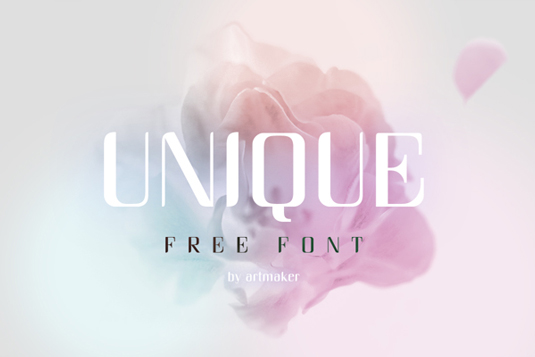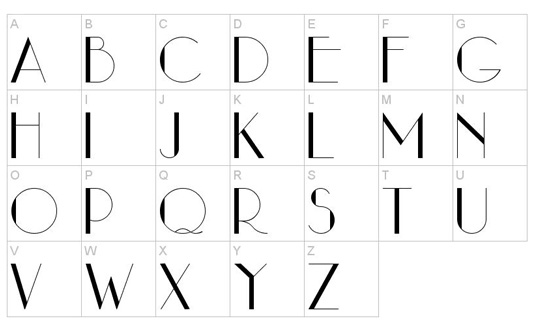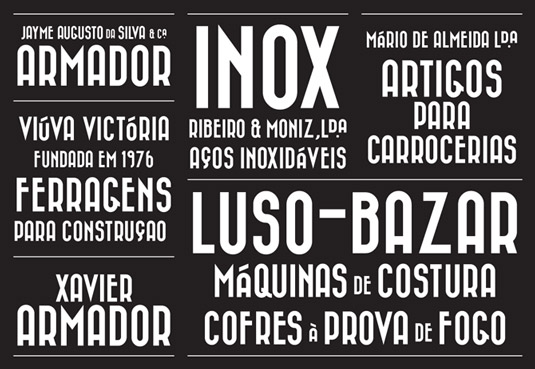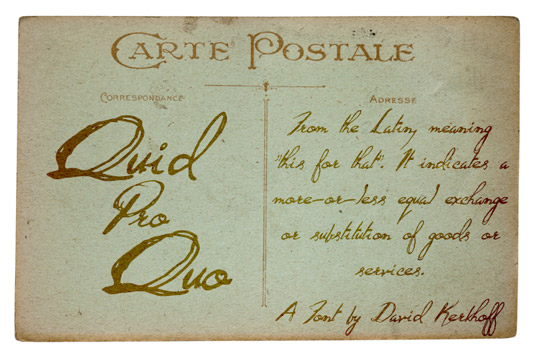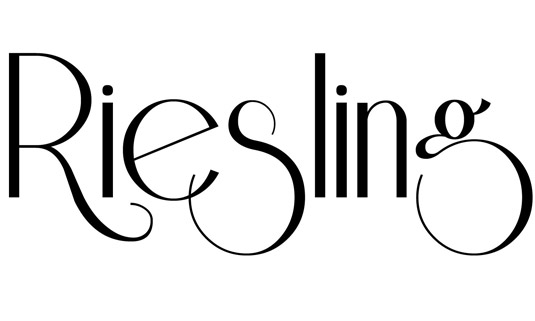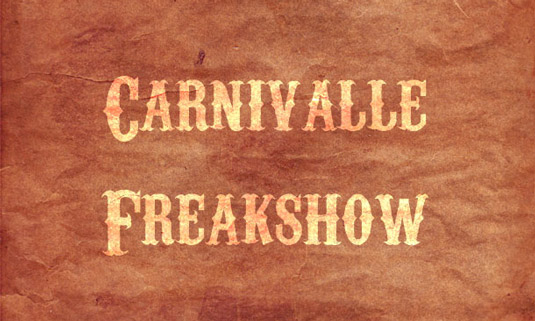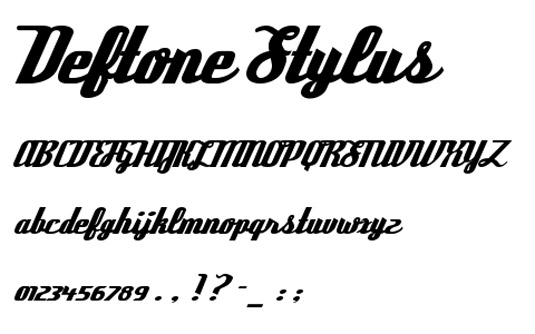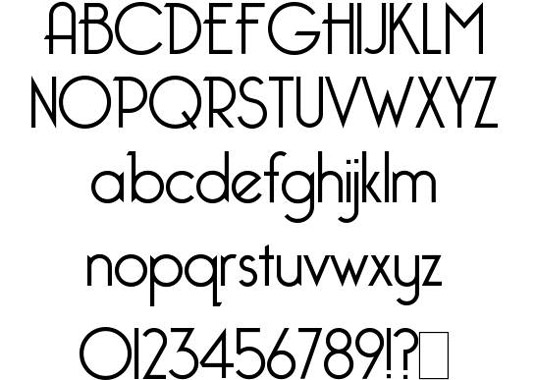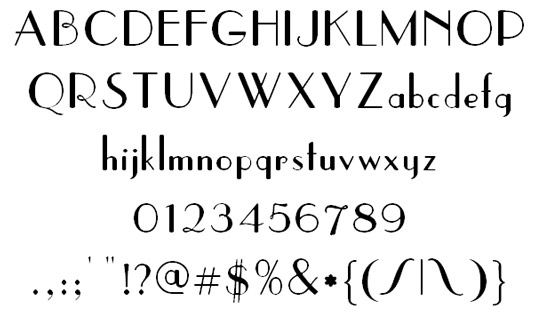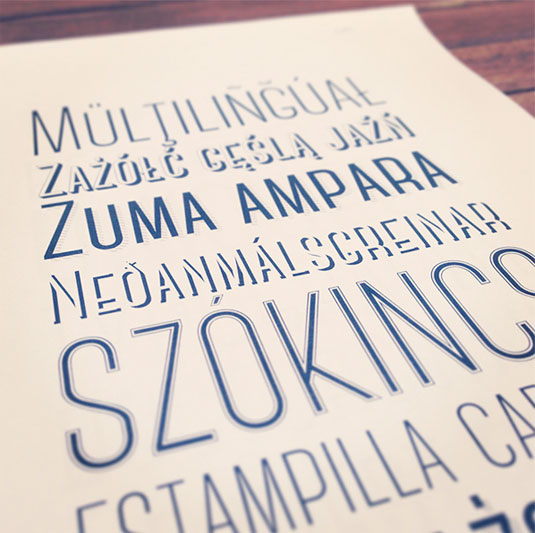
Бесплатные ретро шрифты
Идеей ретро дизайна служит отображение прошлых времен в настоящем или же перенесение зрителя с настоящего в прошлое. В данной подборке собраны ретро шрифты, которые наверняка придутся вам по душе.
01. Unique
02. Vincent
03. Canter
04. Alt Retro
05. Rispa
06. Betty Noir
07. White Rabbit
08. Andes
09. Sesame
10. Arwen
11. Highlands
12. Bazar
13. Quid Pro Quo
14. Pricedown
15. Pompadour Numerals
16. Riesling
17. Carnivalee Freakshow
18. Top Speed
19. Echo Deco
20. Deftone Stylus
21. Bellerose
22. Airstream
23. Parisish
24. Kilogram
25. Budmo